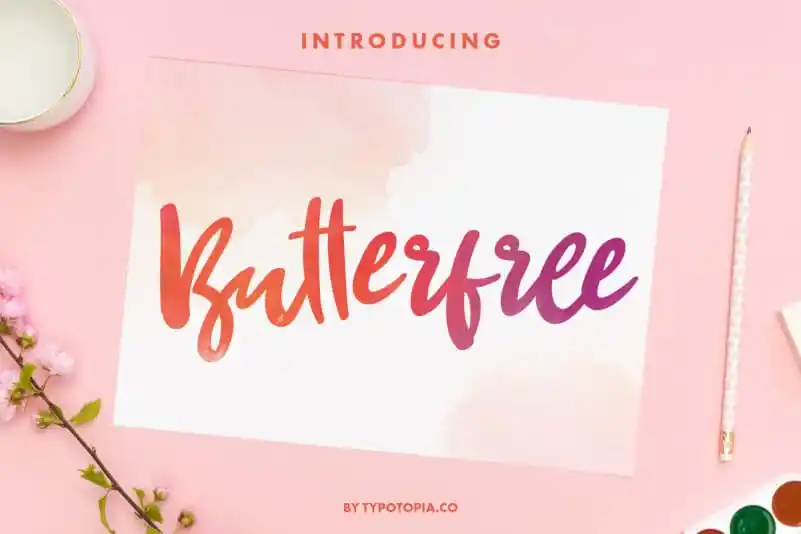
Butterfree Girly Script Font – Download Grátis
A fonte ‘Butterfree Girly Script Font’ é uma escolha irresistível para quem busca personalidade e elegância no design de materiais impressos. Essa curiosa tipografia Brush Fonts foi criada especialmente para aplicação em variados formatos de comunicação gráfica, desde as estilosas identidades corporativas até os mimos mais sutis dos convites de festa. Suas linhas delicadas e fluidas permitem uma expressão única que se adequa perfeitamente aos elementos da sua marca ou evento. Perfeita para criar um impacto visual em materiais publicitários, Butterfree Girly Script é a escolha ideal para quem deseja transmitir estilo através de formatos como cartões de visita, revistas, menus e embalagens. Com sua versatilidade nesse catálogo de categorias, essa fonte se torna um recurso indispensável tanto para designers profissionais quanto para aqueles que desejam dar vida a seus projetos com um toque especial.